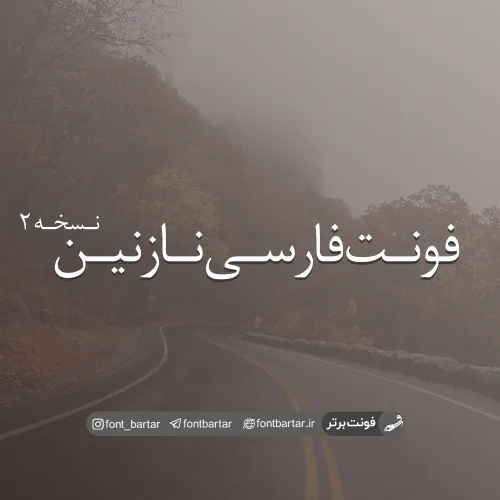
فونت فارسی نازنین
در این مطلب برای شما تایپیستان و گرافیستان عزیز نسخه اصلاح شده و صد در صد یونیکده شده فونت نازنین را قرار داده ایم. فونت نازنین یکی از فونت های پرکاربرد و پرطرفدار در نرم افزارهای ویرایش متن می باشد.
کاربرد و موارد استفاده این فونت بسیار زیاد است که از جمله آن ها می توان به انواع نامه نگاری های اداری و شرکتی ، تایپ انواع مقالات و پایان نامه ها و پروژه های دانشجویی و … اشاره کرد. این نسخه که پیش روی شماست نسخه 2 اصلاح شده این فونت است که کاملا مناسب جهت تایپ متون فارسی می باشد. فرمت فونت نازنین TTF می باشد، پس نصب در سیستم عامل می توانید در کلیه نرم افزارهای گرافیکی و یا ویرایش متن مانند مجموعه نرم افزاری آفیس ، فتوشاپ و … از آن استفاده کنید.
ویژگی های فونت نازنین :
• نسخه اصلاح شده فونت نازنین 2
• کیفیت بالای فونت
فونت نازنین مورد استفاده برای:
• طراحان وب سایت و گرافیست های خلاق می توانند از این مجموعه زیبا فونت در طراحی پروژه های تبلیغاتی و تجاری خود کمک بگیرند.